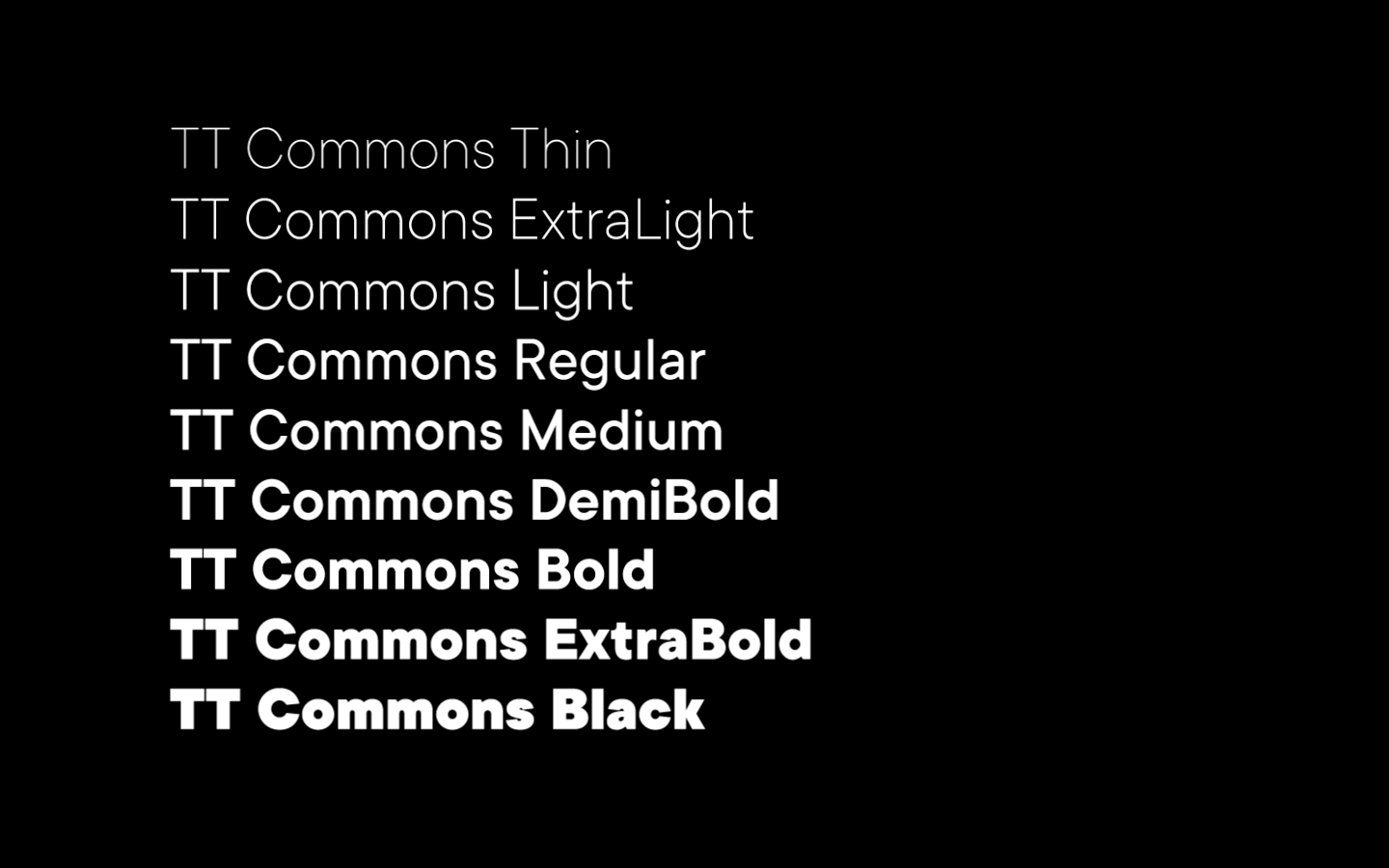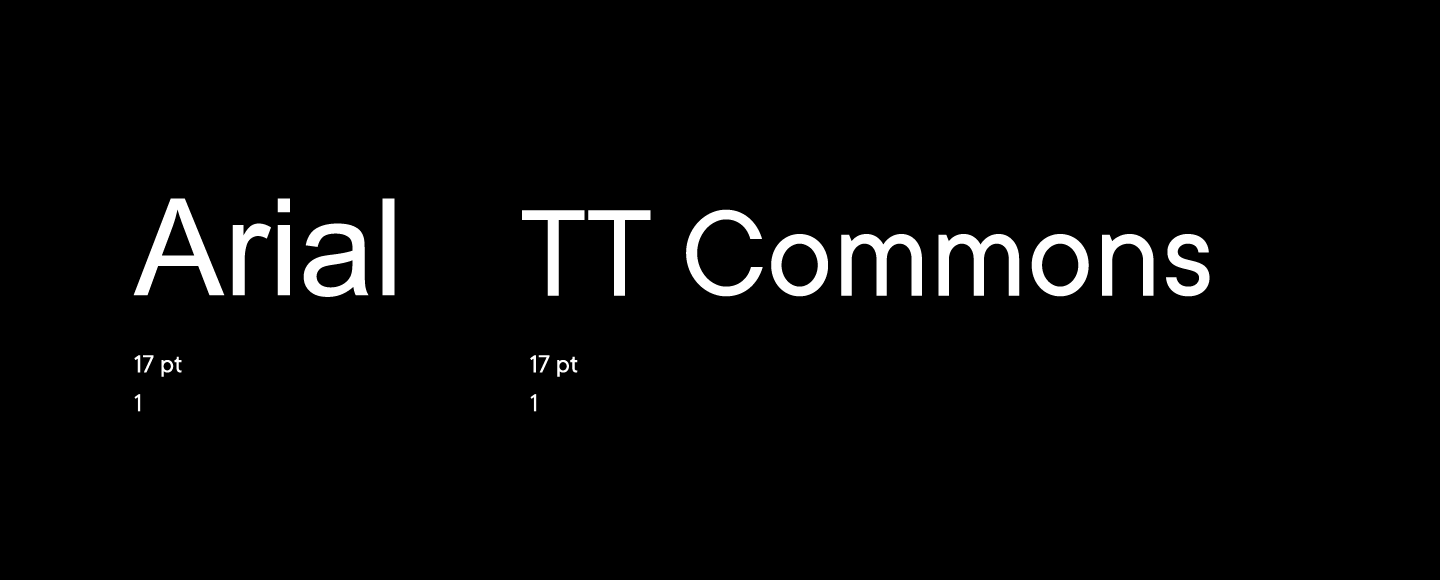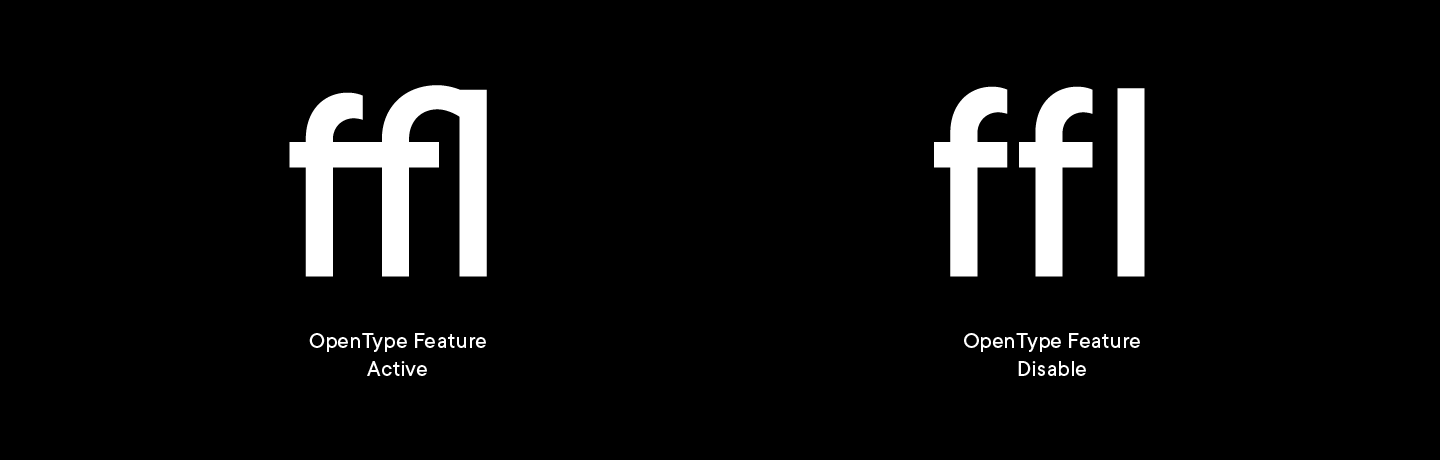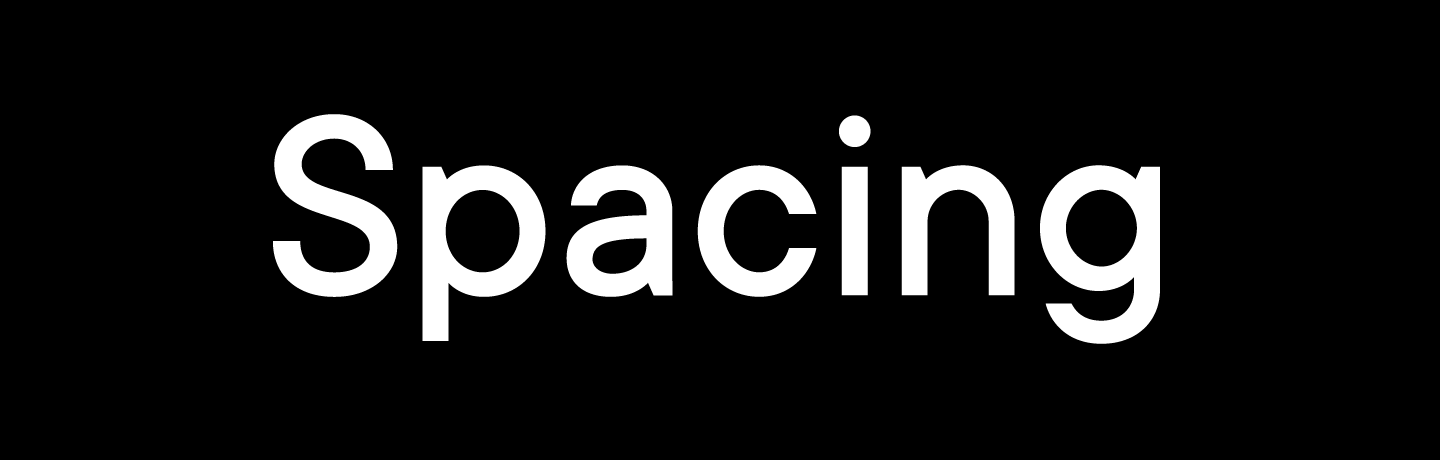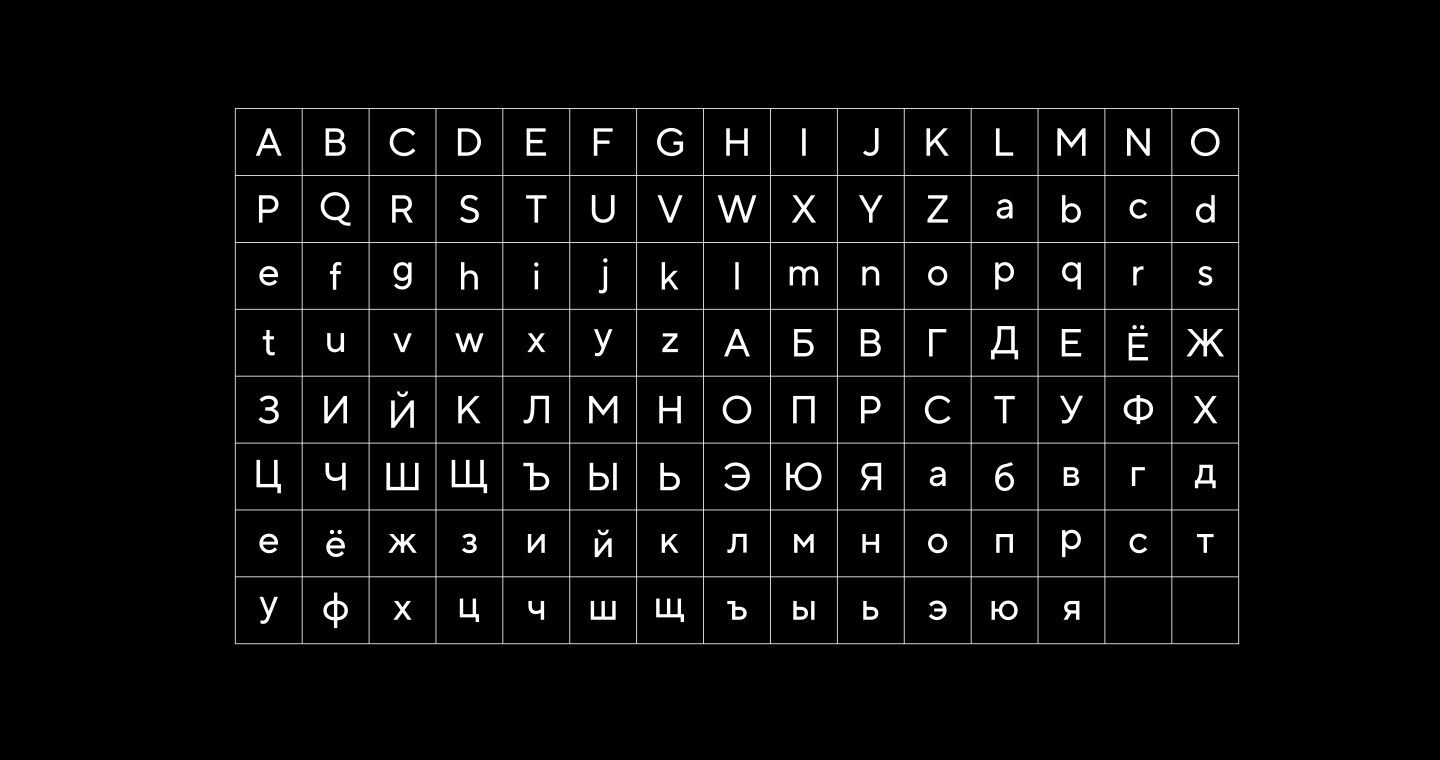
12 способов кастомизировать шрифт
Кастомизация — инструмент для решения огромного списка задач дизайна и отстройки фирменного стиля бренда.
Часто случается, что существующие шрифты не отвечают требованиям конкретного проекта. Но шрифт — это не статичный инструмент, который функционирует только в том виде, в котором он создан. Чтобы передать индивидуальный голос компании, шрифт можно и нужно подстраивать и кастомизировать под свои нужды, начиная от таких простых изменений, как сокращение кассового состава, до сложных изменений дизайна всех глифов.
Мы постараемся в этой статье рассказать обо всех видах кастомизации и задачах, которые можно решить с ее помощью.
Техническая кастомизация
1. Изменение параметров шрифта под референсный шрифт
Начнем с довольно распространенного примера — пропорционального изменения размера шрифта. Например, вы используете на своем сайте системный шрифт, но в какой-то момент решаете отказаться от него и купить шрифт, более подходящий под специфику вашей работы. Но вот проблема: вы заменяете на своем сайте системный шрифт на новый, и верстка портится настолько, что можно делать новый макет.
Причины могут быть разные, и одна из них заключается в том, что физические размеры этих двух шрифтов могут значительно отличаться.
Для такого случая можно сделать кастомную версию, в которой мы просто подгоним размер шрифта либо любые другие метрики под референсный шрифт, чтобы сделать переход между ними максимально легким.
Изменение параметров шрифта TT Commons под референсный шрифт
2. Отключение или кастомизация OpenType features
Современные шрифты являются универсальными продуктами, и в их файлах всегда больше знаков и фич, чем это нужно среднестатистическому дизайнеру.
По умолчанию в шрифты включены OpenType features — например, такие как лигатуры, созданные для знаков, которые сливаются в наборе, чтобы набор был равномерным. В нашей практике много случаев, когда они не нужны клиентам, тогда мы можем их отключить в коде шрифта на своей стороне и передать вам готовый файл.
Отключение или кастомизация OpenType features
3. Изменение спейсинга в шрифте
Спейсинг — расстояние между буквами. В зависимости от задачи мы можем сделать набор текста более плотным или, наоборот, разряженным. Мы были удивлены, когда поняли, что не все дизайнеры знают о подобной кастомизации и тратят много времени, чтобы скорректировать это вручную. Мы бы хотели это исправить!
Приведем интересный пример. Для одного из наших IT-клиентов мы провели исследование и разработали систему изменения плотности набора текста от размера шрифта. По результатам исследования мы сделали 8 шрифтов с разной разрядкой текста, чтобы в более крупном тексте шрифт был плотнее, а в мелком — разряженнее. Таким образом, мы упростили работу клиенту: больше нет необходимости вписывать параметры разряженности текста вручную.
Изменение спейсинга в шрифте
Изменение спейсинга в шрифте
4. Сокращение кассового состава гарнитуры
Продолжаем говорить о размерах и перейдем к физическим параметрам самих шрифтовых файлов, что особенно актуально в современном веб-дизайне.
Один из способов борьбы с весом шрифтового файла — сокращение его кассового состава. Предположим, вам нужен маленький размер шрифтового файла и при этом вы точно знаете, какие языки, цифры и знаки пунктуации вам нужны. В таком случае можно сделать кастомную версию шрифта с сокращенным кассовым составом, оставив только то, что действительно нужно для работы, и тем самым значительно уменьшить вес.
Сокращение кассового состава гарнитуры
Если мы продолжаем гнаться за весом файла, вспомним о вариативности. Если вы планируете использовать на своем сайте более трех прямых начертаний из одного шрифтового семейства, тогда можно разработать и использовать один вариативный файл, который будет покрывать эти три промежутка.
Но это еще не все. Если сокращение кассового состава не помогло, мы можем перейти к глубинной оптимизации: постепенно резать хинтинг, кернинг и найти пару кб, запрятанных в фонт инфо, пока не придем к нужной цифре.
5. Кастомизация средней линии, межстрочного расстояния
Графические редакторы, в которых работают дизайнеры, имеют разный интерфейс, причем не только с точки зрения наполнения, но и с точки зрения специфики выравнивания элементов внутри блоков. Из-за этого шрифты могут отображаться некорректно, и дизайнеру приходится вручную менять параметры, что занимает много времени, которое пригодится для решения более важных задач.
Отличным примером может служить абстрактный объект «Кнопка», внутри которого дизайнер интерфейсов помещает текстовую строку. Чтобы она в различных интерфейсах выравнивалась по центру, необходимо индивидуально настроить параметры ascender и descender внутри шрифта.
Кастомизация средней линии
Похожая проблема часто возникает с межстрочным расстоянием (интерлиньяжем). Кастомизация позволяет настроить любое необходимое вам расстояние между двумя соседними строками, чтобы не делать это вручную каждый раз.